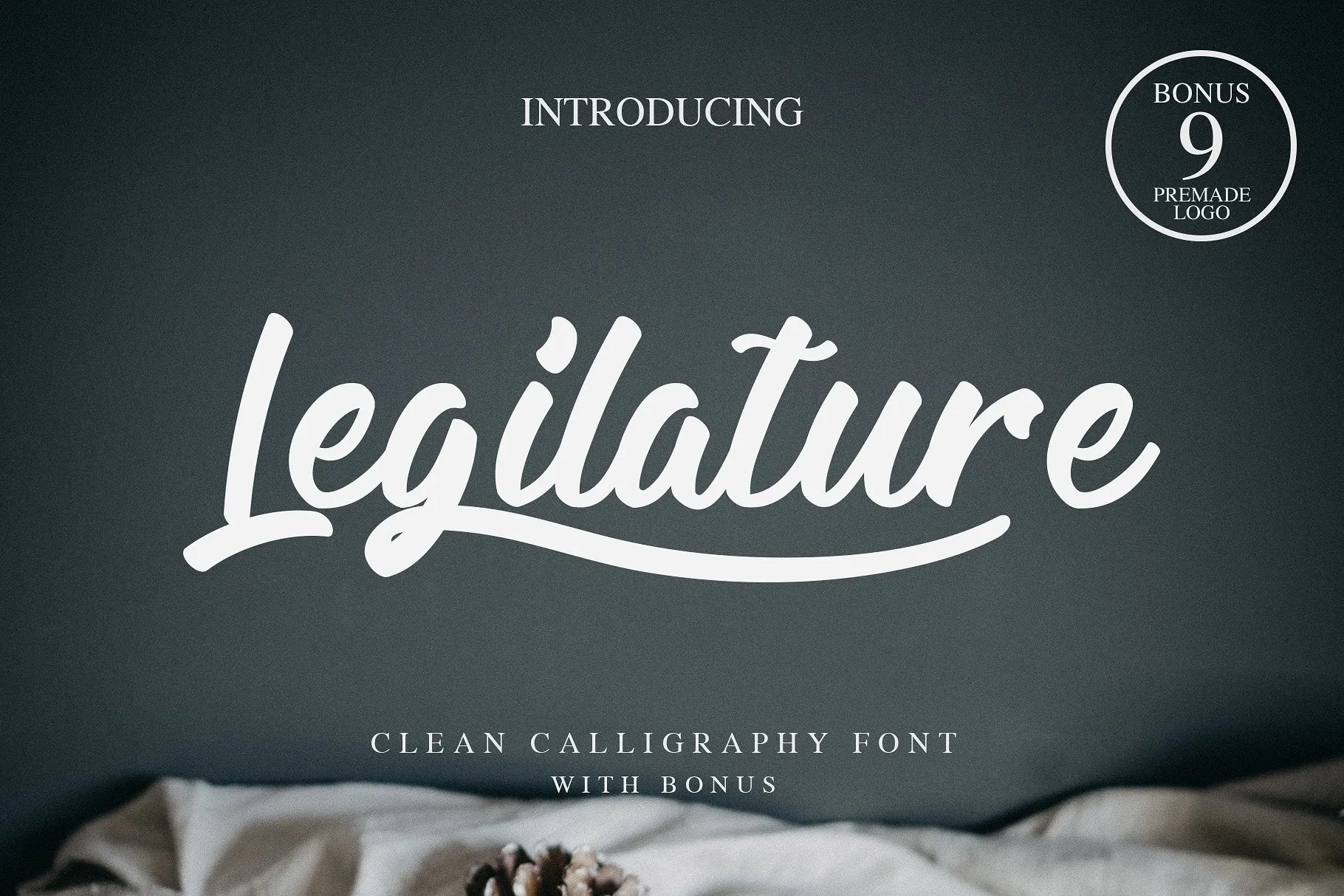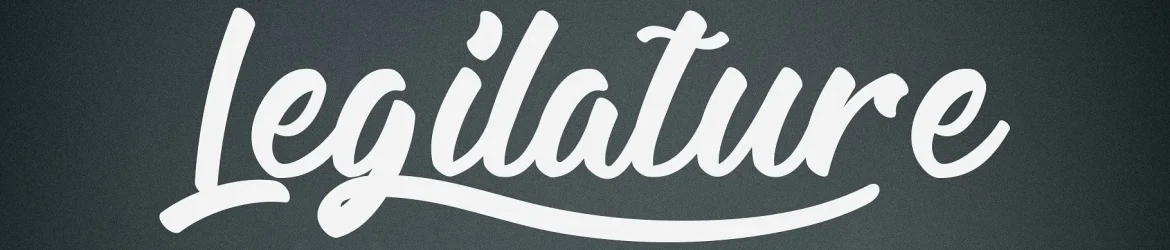
A Legilature Script Font é uma opção elegante para designers que buscam incorporar estilo moderno na sua próxima peça gráfica. Com seu design limpo e clássico, ela se adapta perfeitamente a projetos como cartões de visita, capas de álbuns ou até mesmo as mais criativas palavras de citação. Esta fonte é ideal para quem busca um estilo sofisticado que não abraça a estilização exagerada do calligrafia, mas oferece ao designer uma maneira fácil e prazerosa de adicionar detalhes chamativos às suas criações. A Legilature Font é o tipo de recurso gráfico ideal para aqueles buscando um equilíbrio entre modernidade e elegância na sua arte digital.